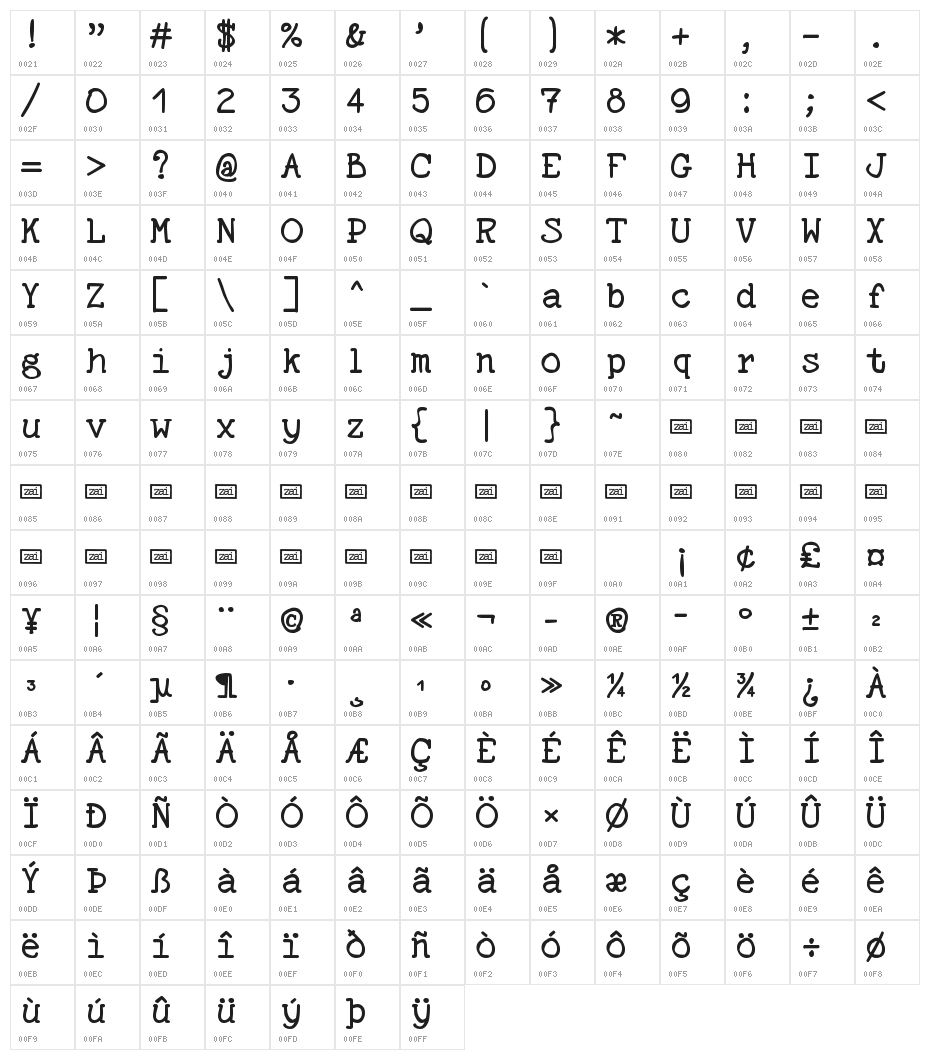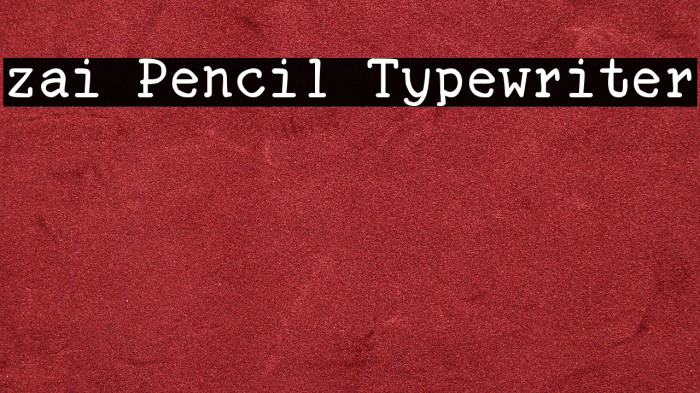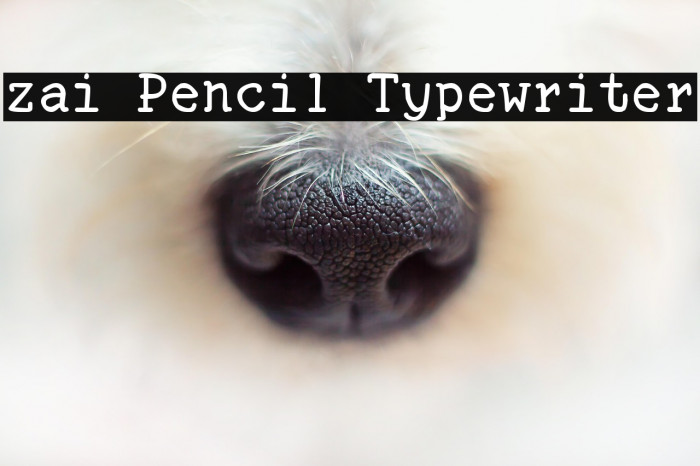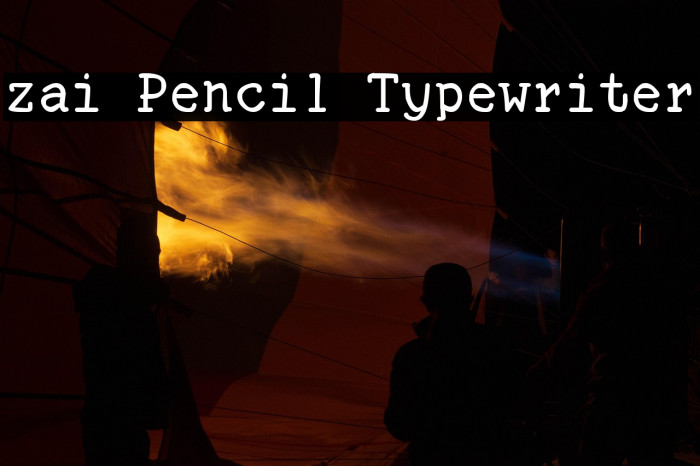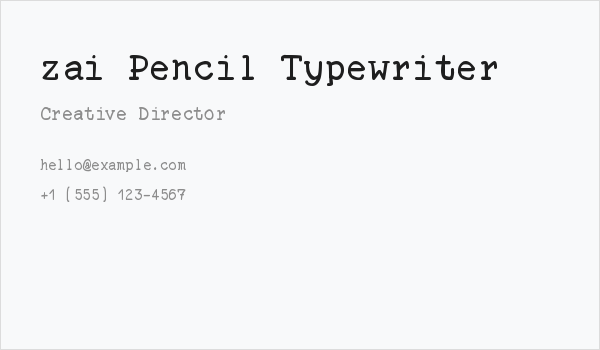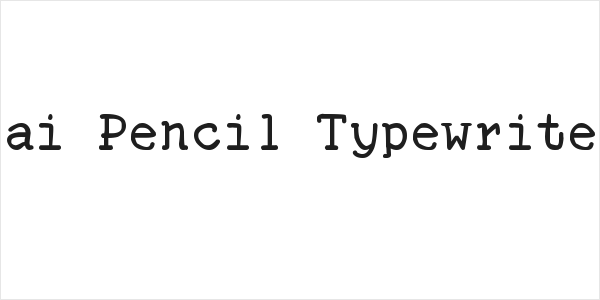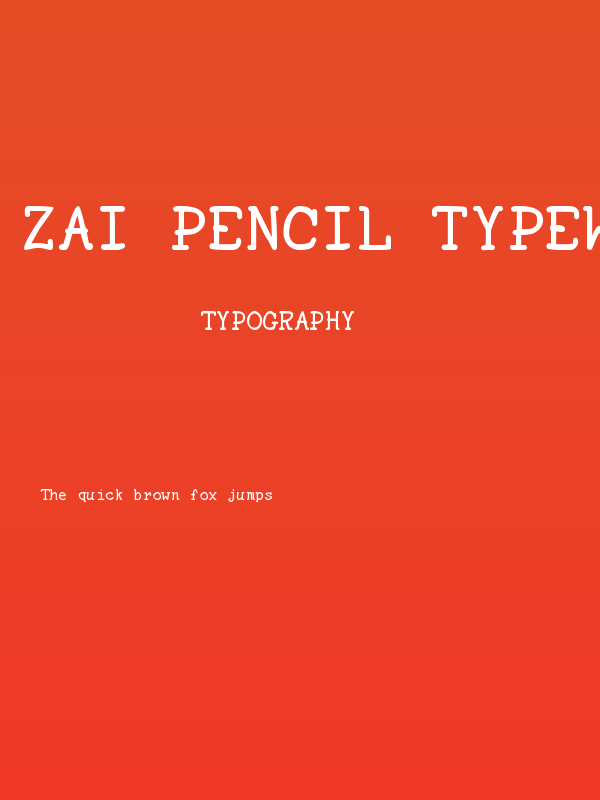
zai Pencil Typewriter Font
| Stile generale | Casual |
| Caso d'uso | Headlines, Logos, Informal Text |
| Progetti proposti | Ideal for creative projects such as greeting cards, invitations, children's books, and casual branding. |